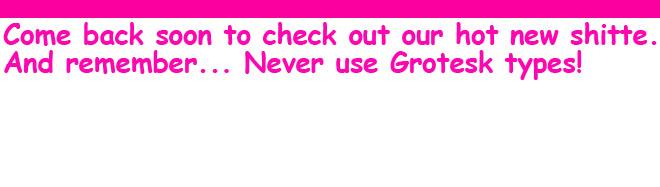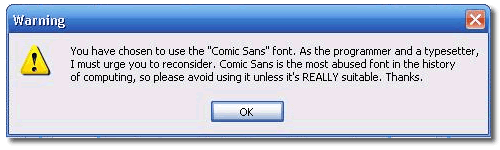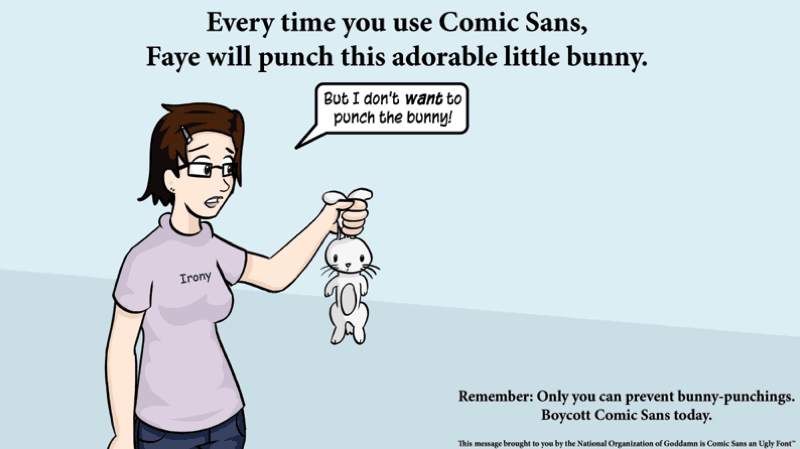
Comic Fonts (war: Wer das liest ist doof)
Meine Meinung: Wie immer ist es die einfache Verfügbarkeit. Vorinstalliert. Gratis. Ohne Nachzudenken zu verwenden. Und ein wenig anders. Da steht ganz groß "Das ist jetzt aber nichts Offizielles!" drauf. Oder aber auch "Das ist für Kinder!" Ich habe noch keinen Kinderarzt bei uns gesehen, der nicht in Comic Sans schreibt.
100% übereinstimmung mit meiner meinung und ich füge hinzu: sie fängt mit C an, steht also in der schriftenliste ziemlich weit oben. der verbraucher sucht eine lustige schrift und fährt seinen schriftenmenü ab – COMIC SANS – STOP! – schrift gefunden aufgabe erfüllt. ähnlich stelle ich mir das bei der arial oder der avantgarde vor. hätte man damals einer anderen schrift den namen arial verpasst, wäre diese wahrscheinlich heute eine der meistengenutzten schriften. oder noch besser, hätte microsoft damals nicht bei der helvetica abgeschaut sondern bei der univers hätten wir heute überall universclone. arivers oder so.
* Das »S« oben ist Unfug. Niemand schreibt so ein »S«. Ich erwarte von so einer Schrift aber, daß sie auf mich wirkt wie echt geschrieben.
das würde ich so nicht sagen, ich fange mein S von unten an, an der serife. also strich nach oben und einen S-linie daran, fertig.
Ich habe als Kind und Jugendlicher so ungefähr zwei Kubikmeter Sprechblasenliteratur angehäuft: "S" und "!" in der Alterego entsprechen 100 % dem Handlettering (amerikanischer) Comics. Bei franko-belgischen Comics sieht das wieder anders aus. (Irgendwo kursiert im Netz sogar ein Font, der auf dem Handlettering von Carl Barks basiert - selbst den könnte man für "künstlich" halten - aber es sind eben "Kunstschriften"). Und auch die "Kursive" wird gern verwendet, z.B. wenn Spiderman grübelt oder Aliens in alienisch reden (dann sind aber meist noch die Sprechblasen komisch umrandet). Das wurde schon früh (per Hand) so gemacht. Aber vielleicht ist das ja ein Sympathiemerkmal der Comic Sans: "Mutti, schau ich hab da meinen ersten Comic gelettert."
Kann es nicht auch so sein, daß bestimmte Leitfiguren in der Typographie-Szene eine Art Lemming-Effekt erzeugen, indem sie Dogmen zu Schriften in die Typo-Welt setzen?
Ich hatte mir gestern noch die Kommentare des von Rainer indirekt verlinkten Artikels angetan: das paßt zu Deiner Vermutung. Als gäbe es da viele Mitläufer, die nur mitlästern, weil das ein »sicherer Punkt« ist. Man »kann damit nichts falsch machen.«
sie fängt mit C an, steht also in der schriftenliste ziemlich weit oben
Nun, was das angeht, ist sie in bester Gesellschaft: das Ungleichgewicht eines Schriftenordners, hin zu den Buchstaben am Anfang des Alphabeths, ist im Vergleich zu einem Wörterbuch schon sehr augenfällig.
das würde ich so nicht sagen, ich fange mein S von unten an, an der serife. also strich nach oben und einen S-linie daran, fertig.
Du kannst halt nicht schreiben ... :wink: Nein, okay: sieht das dann auch so unförmig aus?
"S" und "!" in der Alterego entsprechen 100 % dem Handlettering (amerikanischer) Comics.
Okay: ich oute mich: meine Kenntnis von US-Comics reicht nicht über Dilbert hinaus. Aber es erstaunt mich doch, wenn Menschen, die viel schreiben müssen, sich einen Buchstaben mit offensichtlich gehemmtem Schreibfluß angewöhnen. Normalerweise verfestigen sich Schriften ja in die umgekehrte Richtung ...
Danke sehr. Dieser Begriff war mir bis gerade eben völlig unbekannt.
Offenbar (Kinderarzt, Kindergarten, Schule) wird sie also bevorzugt im »kindlichen Umfeld« eingesetzt. Wegen des Comic-Image? Da muß ich mal unseren Ältesten befragen, ob das auch wirklich ankommt.
Das Ergebnis: die Comic Sans funktioniert!
Also: abwegig ist es offenbar nicht, die Comic Sans für Kinder einzusetzen.
Geht es um den Geschmack der Kinder, oder darum, daß sie Texte gut lesen können? Bei einem Achtjährigen spielt der Geschmack anscheinend schon sehr mit rein, aber für einen Leseanfänger sind wohl andere Dinge wichtig, wie kurze Zeilen, passender Zeilenabstand, sinnerhaltende Zeilenumbrüche.
Bei der verwendeten Schrift sollten die Einzelbuchstaben sich ausreichend unterscheiden: Eine Groteskschrift, bei der d und p die selbe Form, nur gedreht, haben, ist tendenziell verwirrender für einen Leseanfänger als eine Serifenschrift, wo die Serifen an d und p dafür sorgen, daß beide eben nicht die »selbe« Form haben.
(»Erste Hilfe in Typografie« hat zu dem Thema eine Doppelseite, ganz ohne Comic Sans.)
Wo sind jetzt also die Comic Sans-Hasser, die mir erklären, was an der Schrift (nicht an der Verwendung) »beschissen« ist?